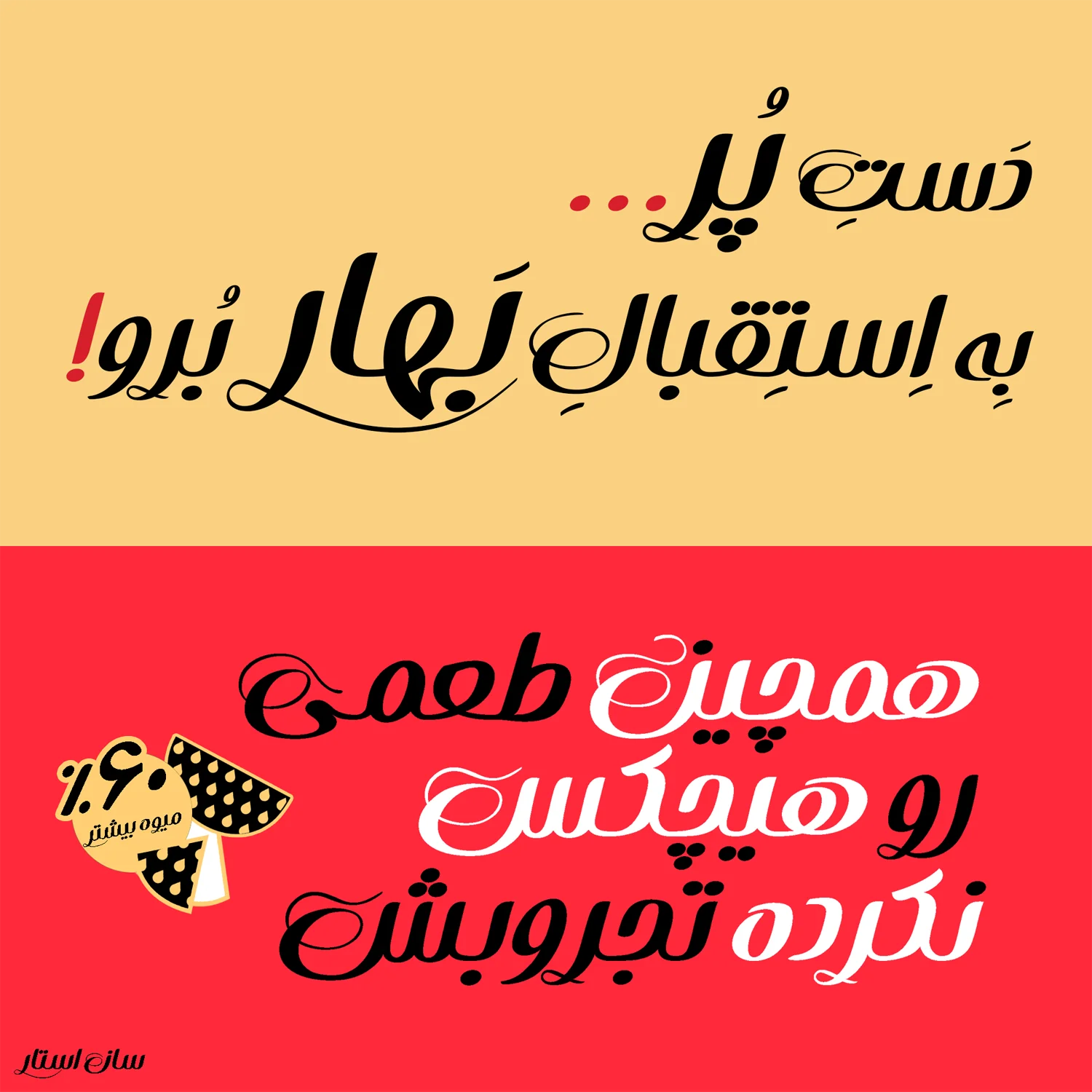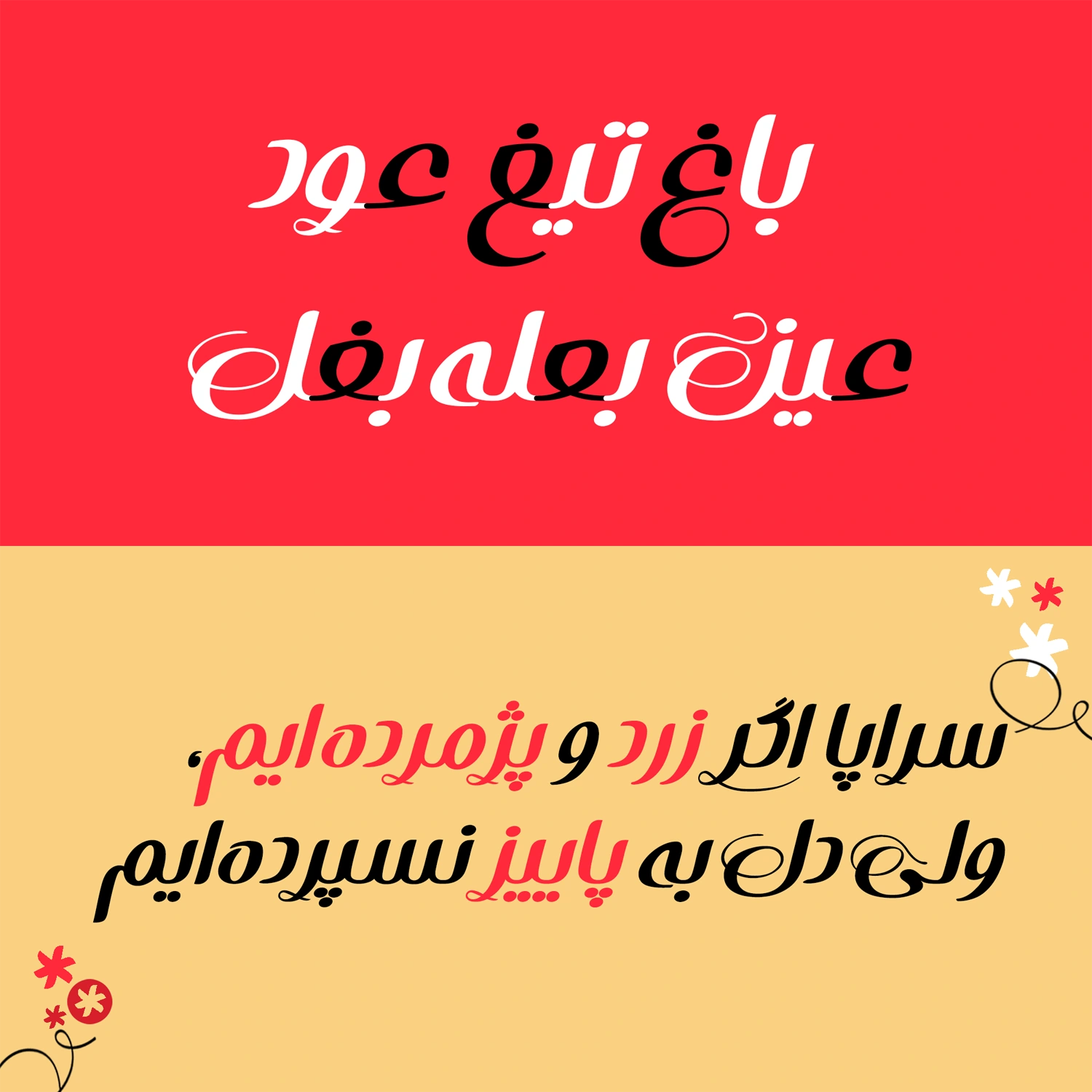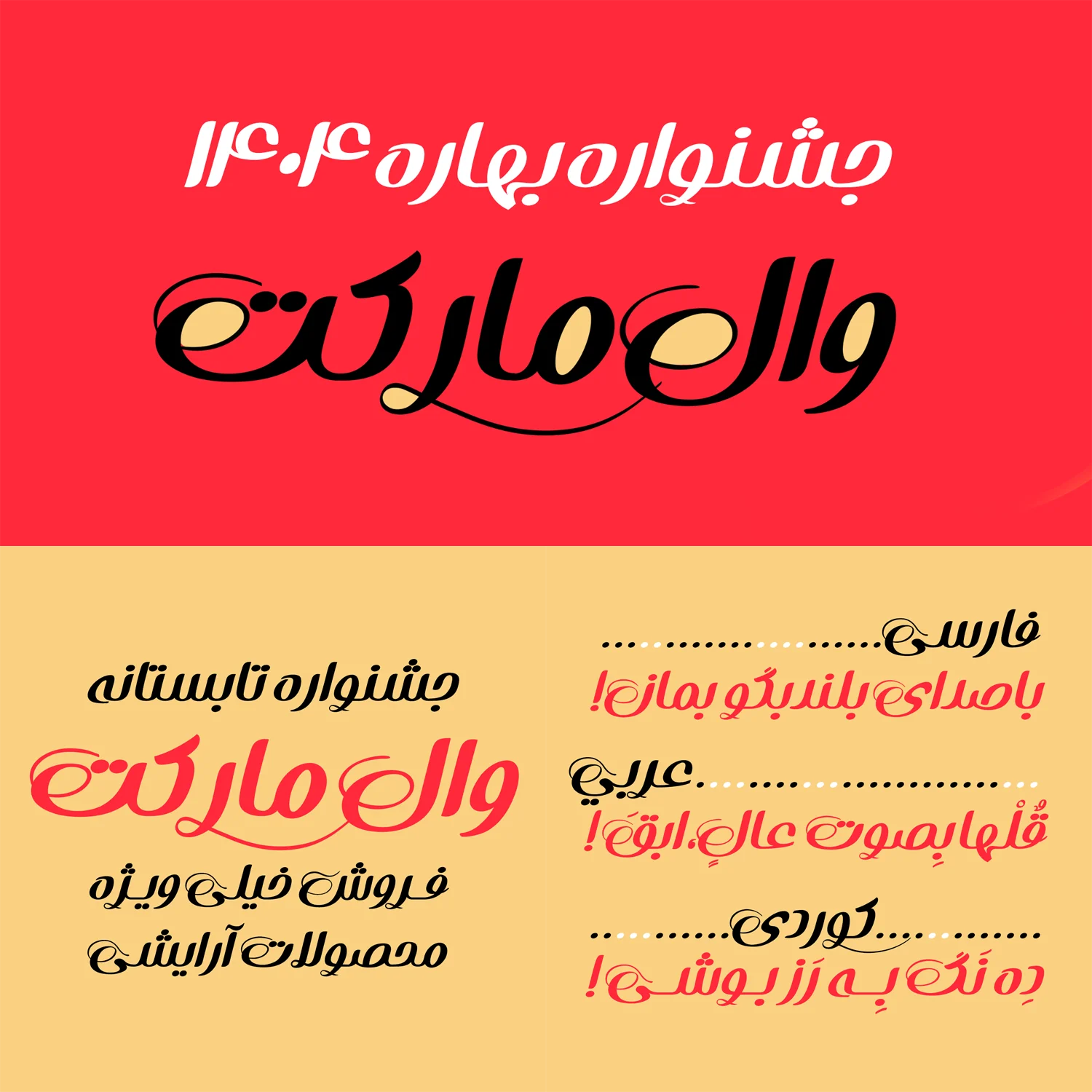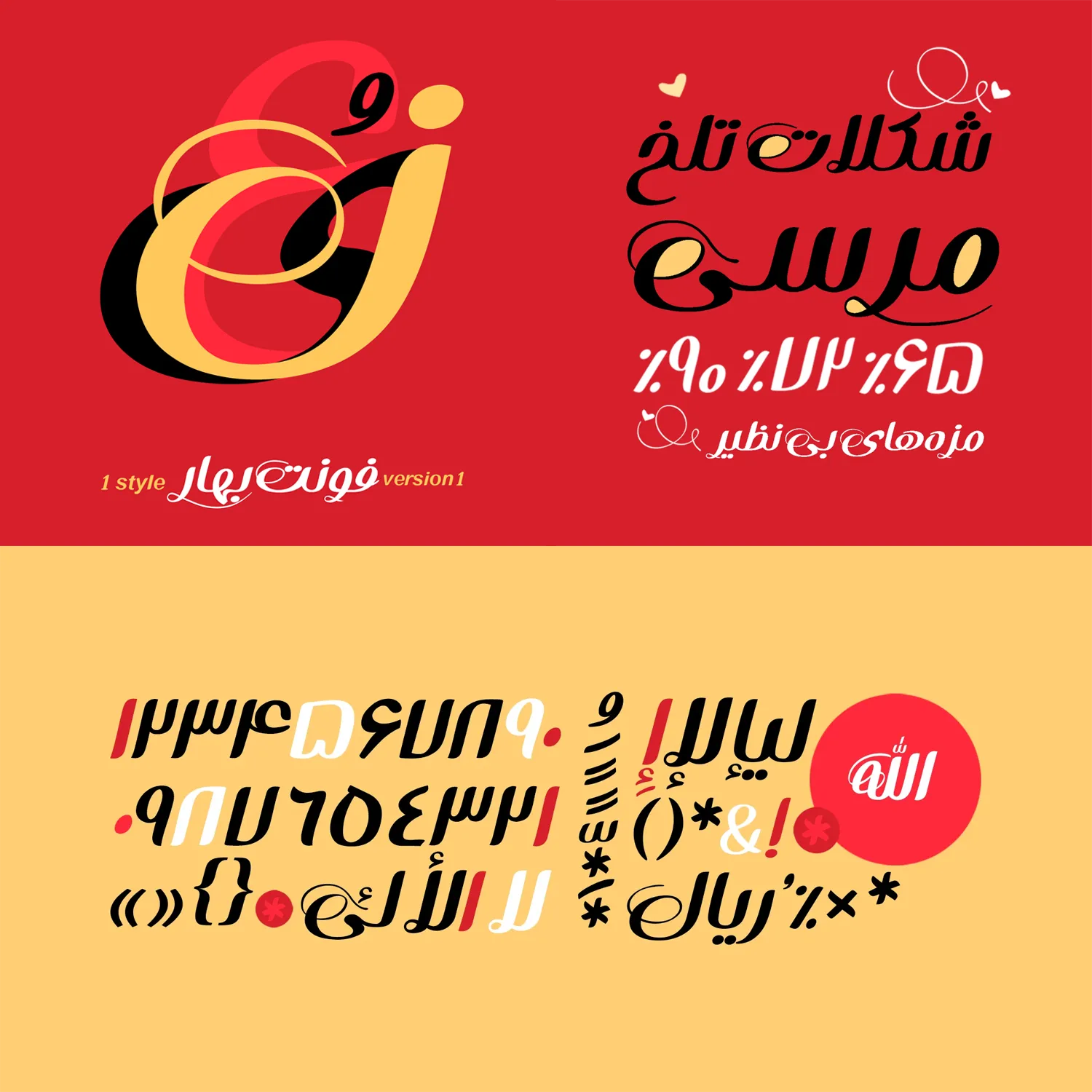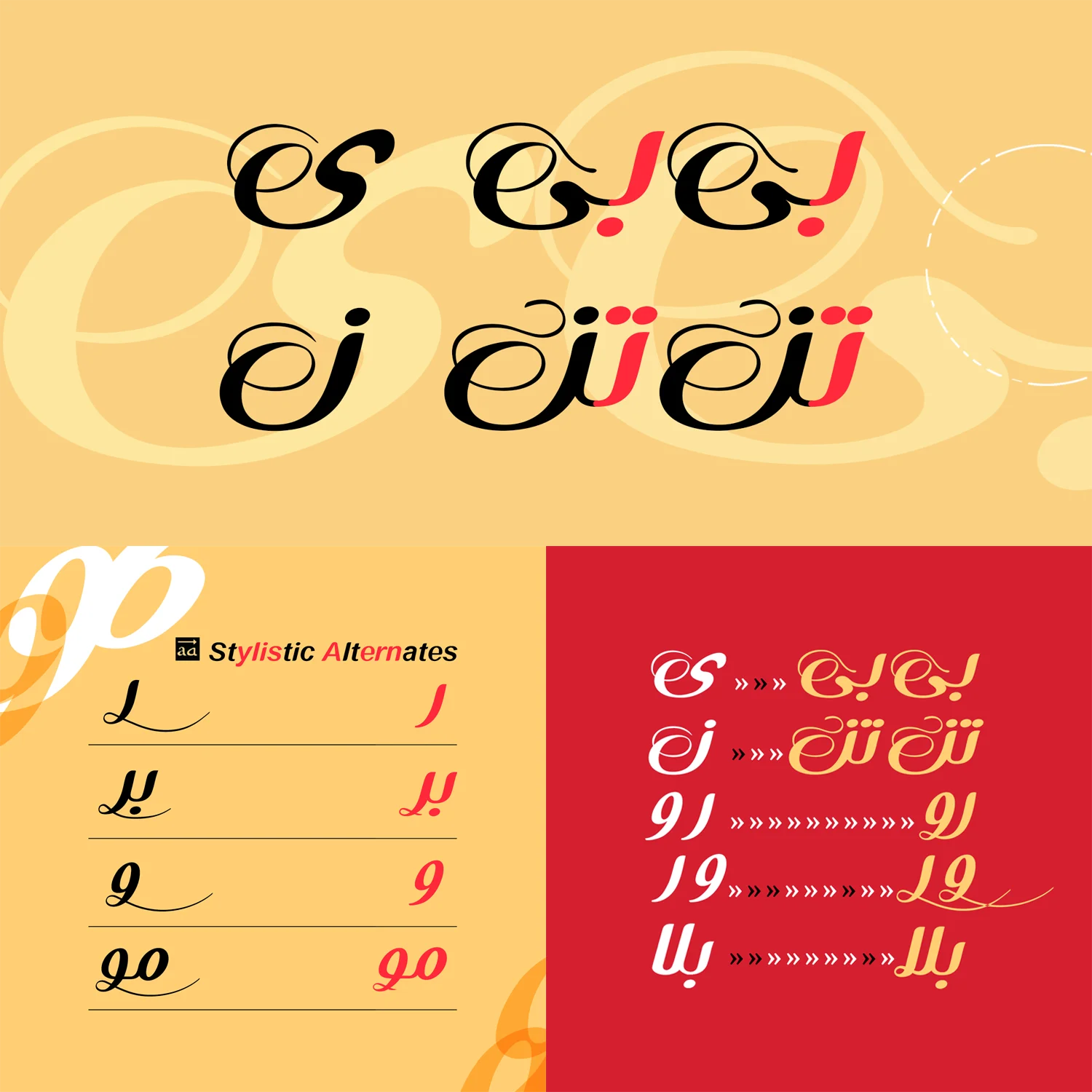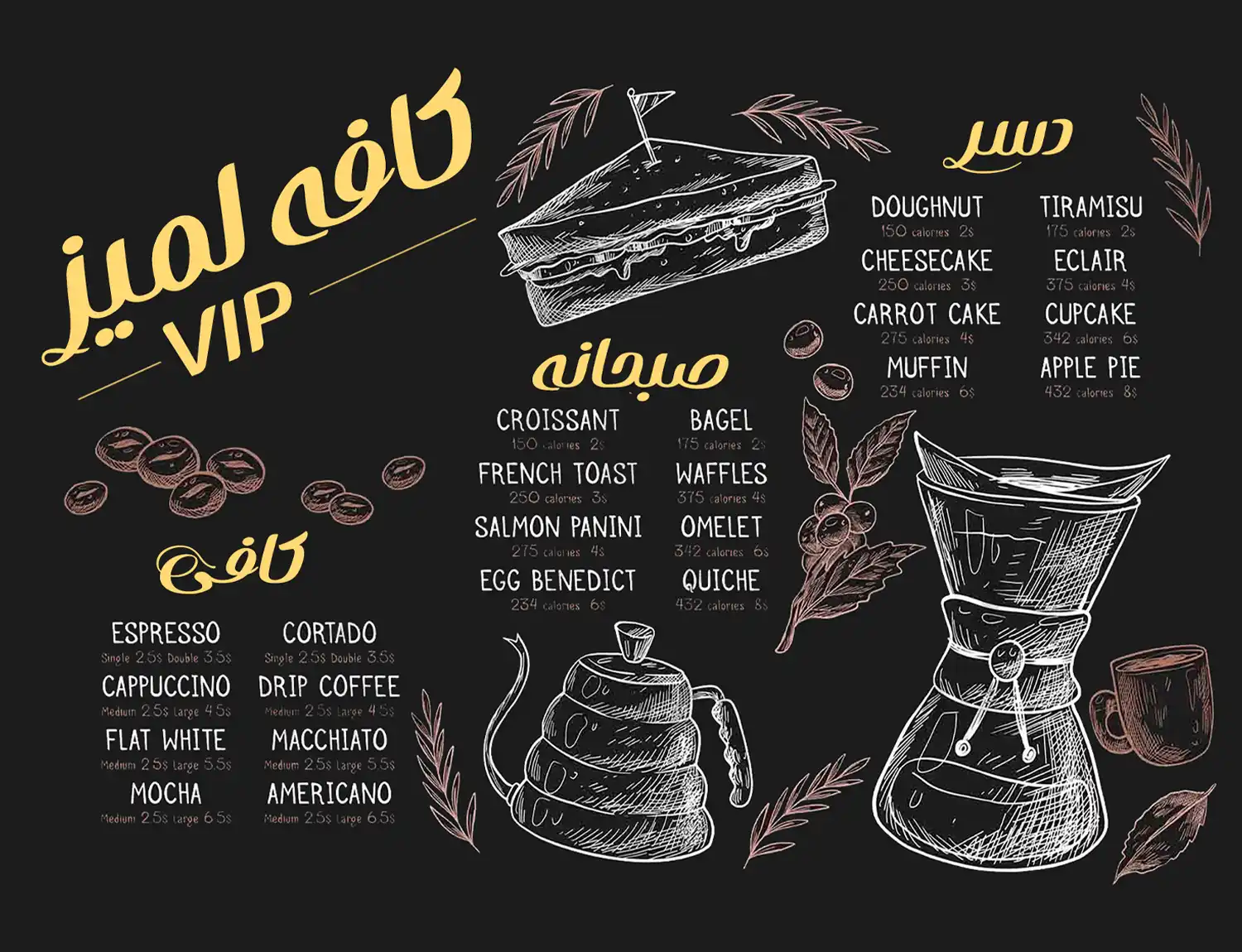
فونت بهار (Bahar)
فونت بهار (به انگلیسی: Bahar) بهعنوان یک فونت فارسی فانتزی و دستنویس، با ساختار منحصربهفرد خود وارد بازار شده و گزینهای ایدهآل برای عناوین، تبلیغات و پوسترها به شمار میرود. اگر به دنبال فونتی هستید که حس مهربانی، بازیگوشی و رهایی را به مخاطبان منتقل کند، بهار دقیقا همان چیزی است که نیاز دارید.
این فونت فارسی جدید که توسط هدی کاسپور طراحی شده، نه تنها از زبانهای فارسی، عربی و کردی پشتیبانی میکند، بلکه با ویژگیهای هنریاش، مرزهای سنتی تایپوگرافی را جابهجا کرده و به یک ابزار قدرتمند برای طراحان تبدیل شده است.
فونت بهار با الهام از کالیگرافی مدرن طراحی شده و خطوط منحنی و فرمهای رقصان آن، حس نزدیک بودن و محبت را القا میکند. قوسهای پیچان انتهای حروف منفصل و متصل از نقاط قوت این فونت فارسی است که به فضاسازی اطراف حروف کمک کرده و همبستگی ترکیببندیها را در لوگوتایپها، تیترها، شعارهای تبلیغاتی و ترکیبهای تایپوگرافی افزایش میدهد.
چنین ساختاری به ایجاد برای برقراری ارتباط احساسی و عاطفی در فضای گرافیکی، کمک میکند. ساختار کلی حروف در فونت بهار فرم لمیده (ایتالیک) دارد، با قوت و ضعف چشمگیر که حالتی خوشنویسیگونه ایجاد میکند. برخلاف سبکهای سنتی مانند نسخ، حروف در قسمت خط کرسی نازک شده و به تدریج ضخیم میشوند، که این روند ساختار را مدرن و لاتینایز میکند.
برخی حروف حتی شبیه به همتایان لاتین خود به نظر میرسند، که این امر فونت را برای پروژههای بینالمللی یا ترکیبی با فونتهای لاتین ایدئال میسازد.
پشتیبانی از زبانهای متنوع
فونت بهار محدود به زبان فارسی نیست. از زبان عربی و کردی پشتیبانی کاملی دارد که شامل تمامی گلیفهای استاندارد برای این زبانها میباشد.
همچنین در بخش اعداد و اعراب این فونت شاهد رعایت استاندارد طراحی هستیم. برای مثال اعداد عربی «۰۴۵۶» که ظاهری متفاوت با اعداد فارسی «۰۴۵۶» دارند، به شکل استاندارد تایپ خواهند شد.
در بخش اعراب نیز شاهد همنشینی درست اعراب در کنار حروف و دیگر اعراب مانند تشدید یا سکون هستیم که این فونت را در دسته فونتهای نمایشی و مناسب عناوین یا تبلیغات، به گزینه مناسبی تبدیل میکند. درست جایی که استفاده از ابعاد بزرگ در نوشتار نیازمند رعایت این موارد هستند.
ترکیبات جایگزین برای طراحی حرفهای
فونت bahar در حروفی مانند «ر» و «و» در حالتهای ساده و کرشمهدار، انعطاف بیشتری دارد. همچنین برخی ترکیبات بهصورت اجباری دارای ساختار کرشمهای است که ظاهر فونت را زیباتر میکند.
از دیگر ویژگیهای فنی فونت بهار میتوان به حروف ترکیبی هوشمند اشاره کرد که برای همنشینی بهتر و اصلاح فواصل طراحی شدهاند. این لیگاچرها در نمونههای تصویری فونت به وضوح قابل مشاهده هستند و به بهبود جریان بصری متن کمک میکنند.
فونت مناسب برای کارهای خلاقانه
فونت بهار با اینکه در یک وزن بولد (Bold) نسبتا ضخیم ارائه شده است، اما با این حال در استفاده در محیطهای مختلف دیجیتال یا فضای چاپ بهخوبی عمل میکند.
برای مثال در طراحی یک پوستر تبلیغاتی برای برندی لوکس، خطوط بازیگوش فونت بهار، حس مثبت و رهایی را به بیننده منتقل میکند و ارتباطی عمیقتر ایجاد مینماید.
با این حال، برای متنهای طولانی یا رسمی، ممکن است سبک فانتزی آن بیش از حد بازیگوش به نظر برسد، بنابراین بهترین کاربرد آن در عناوین و بخشهای برجسته است.